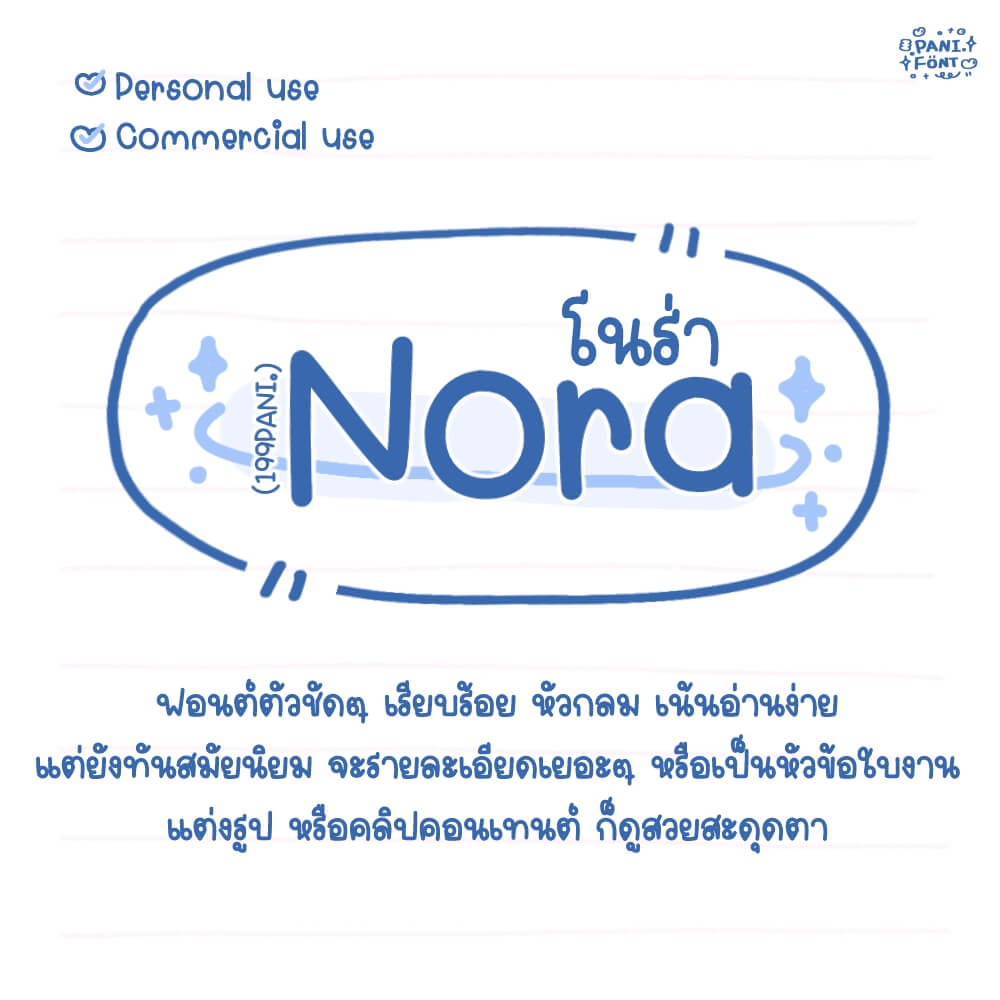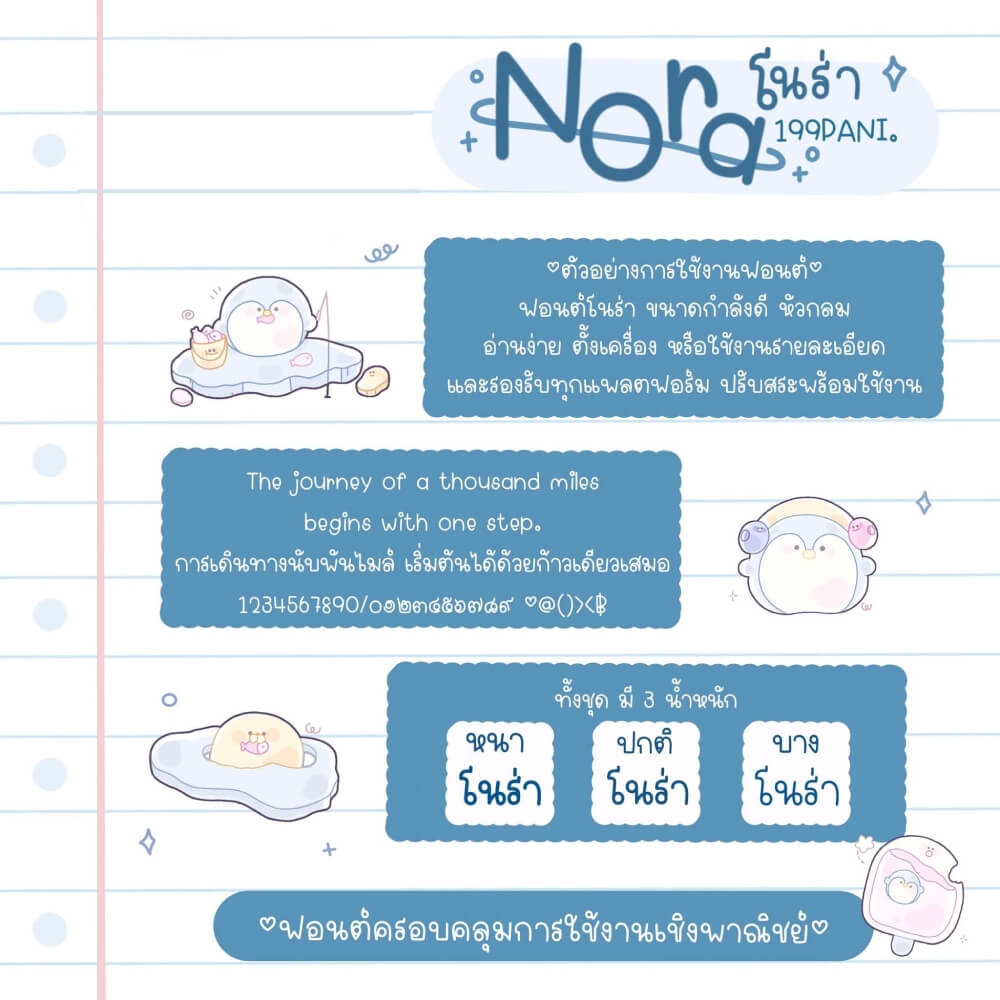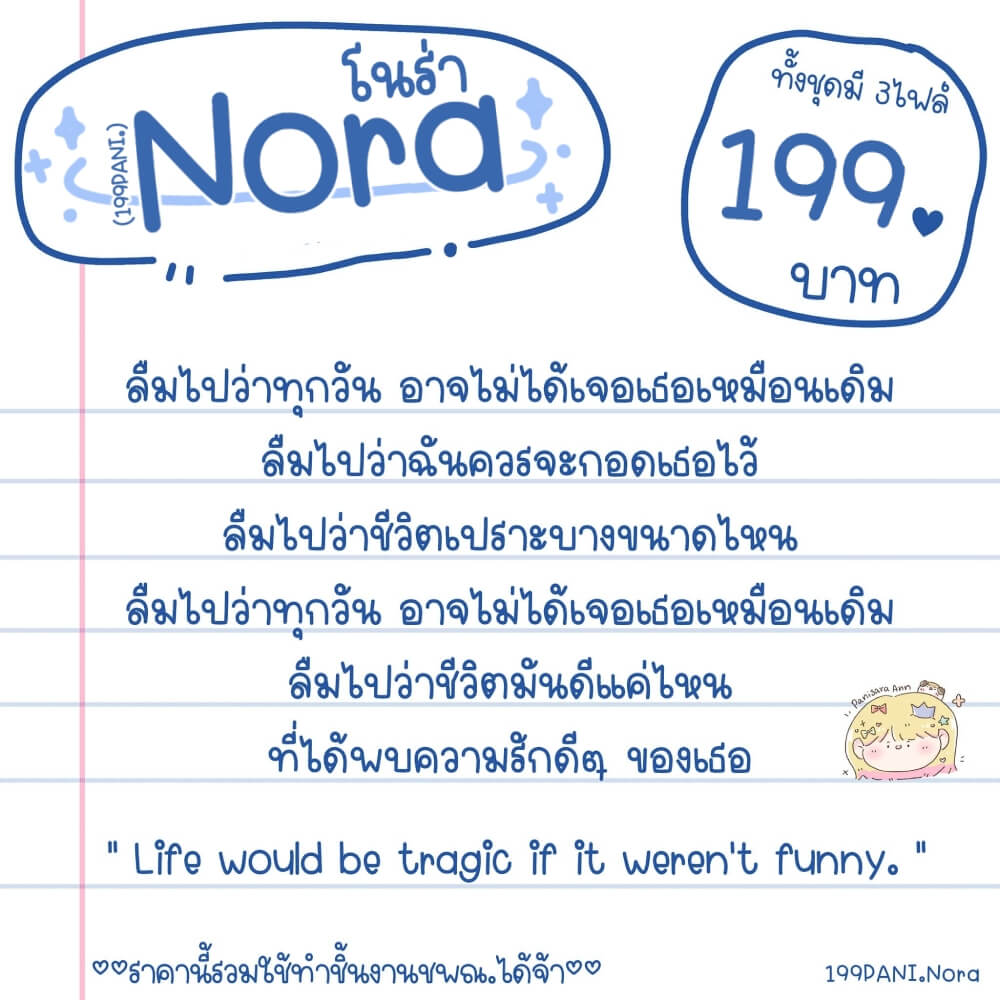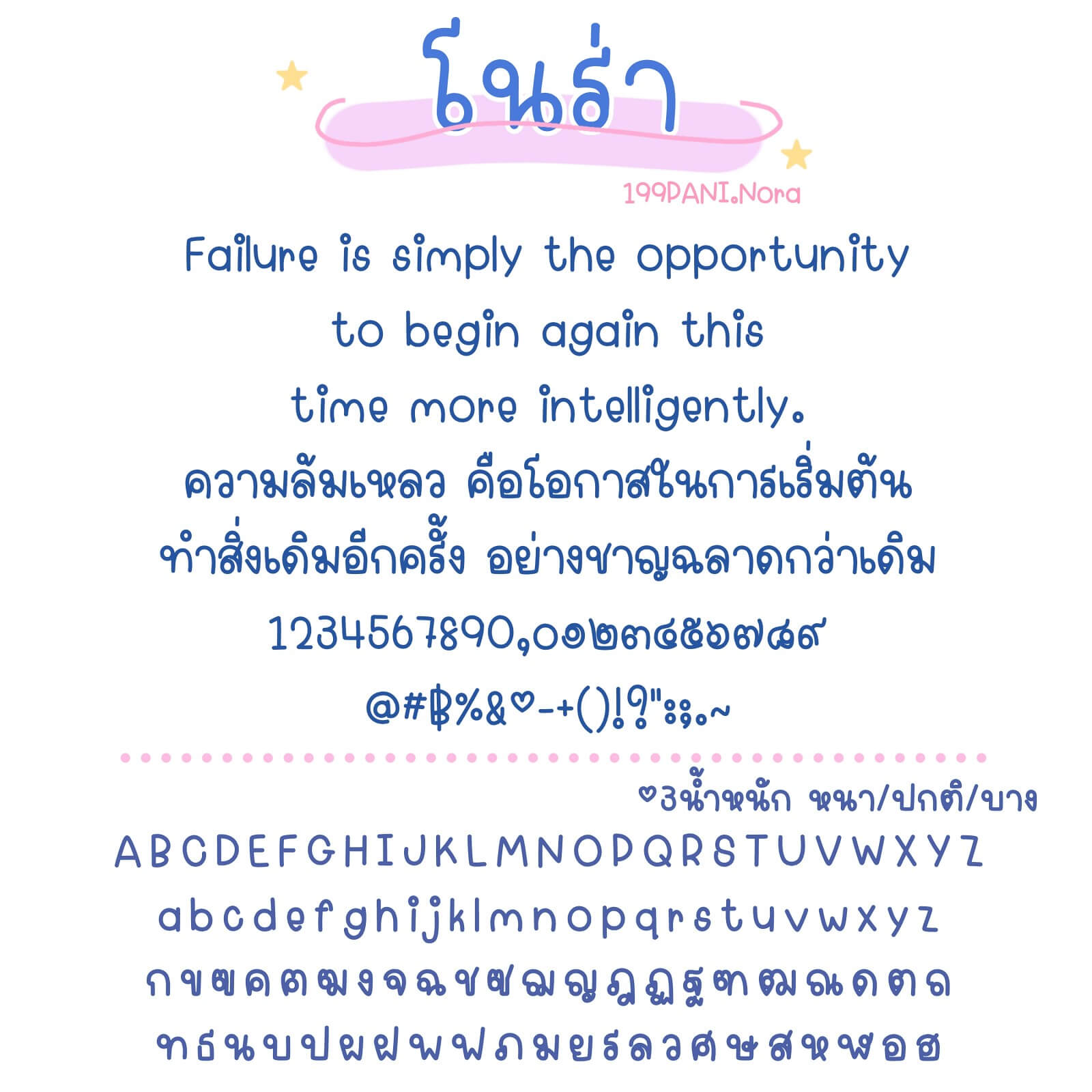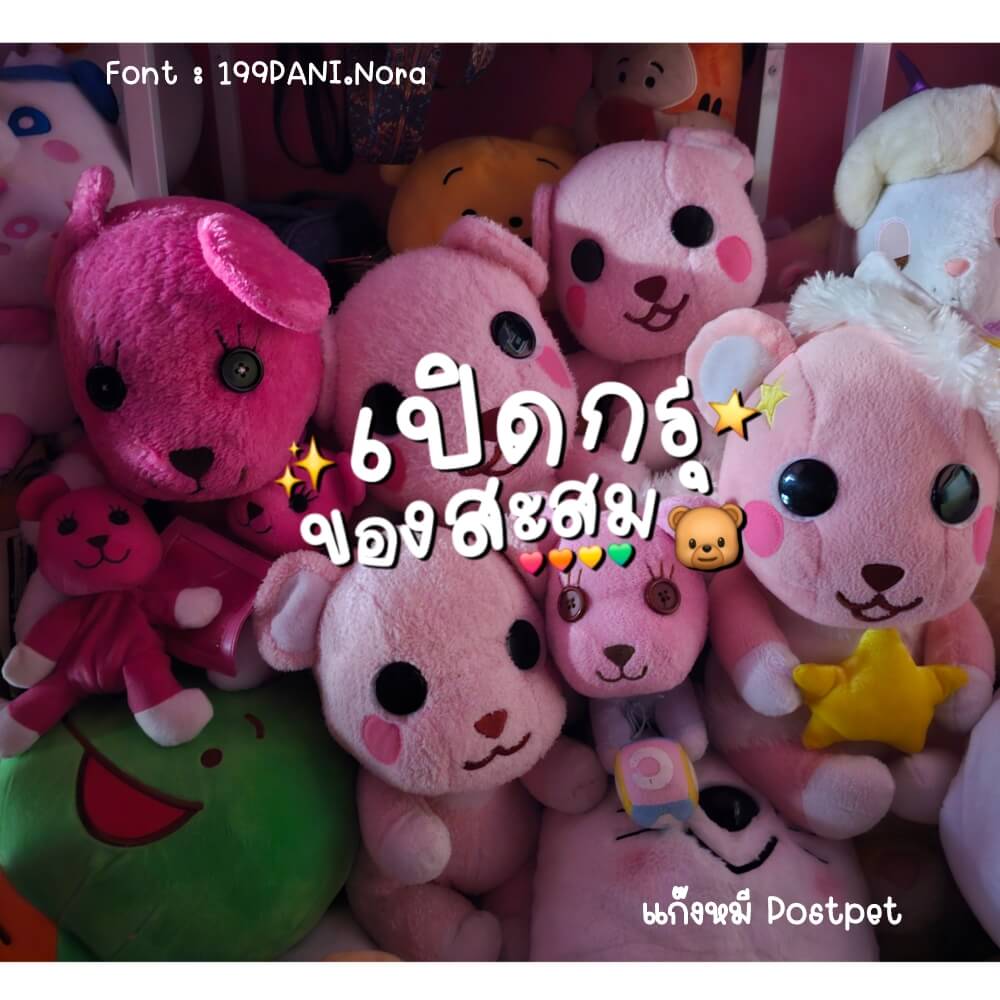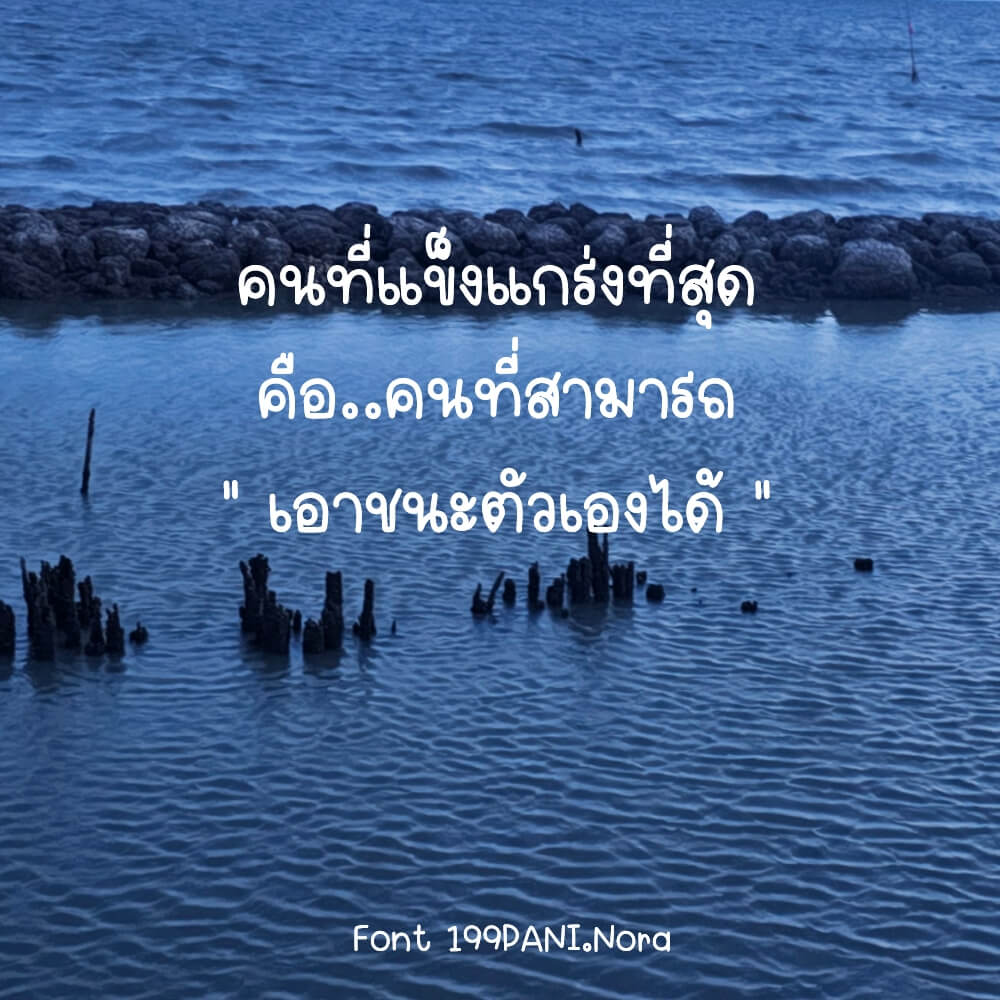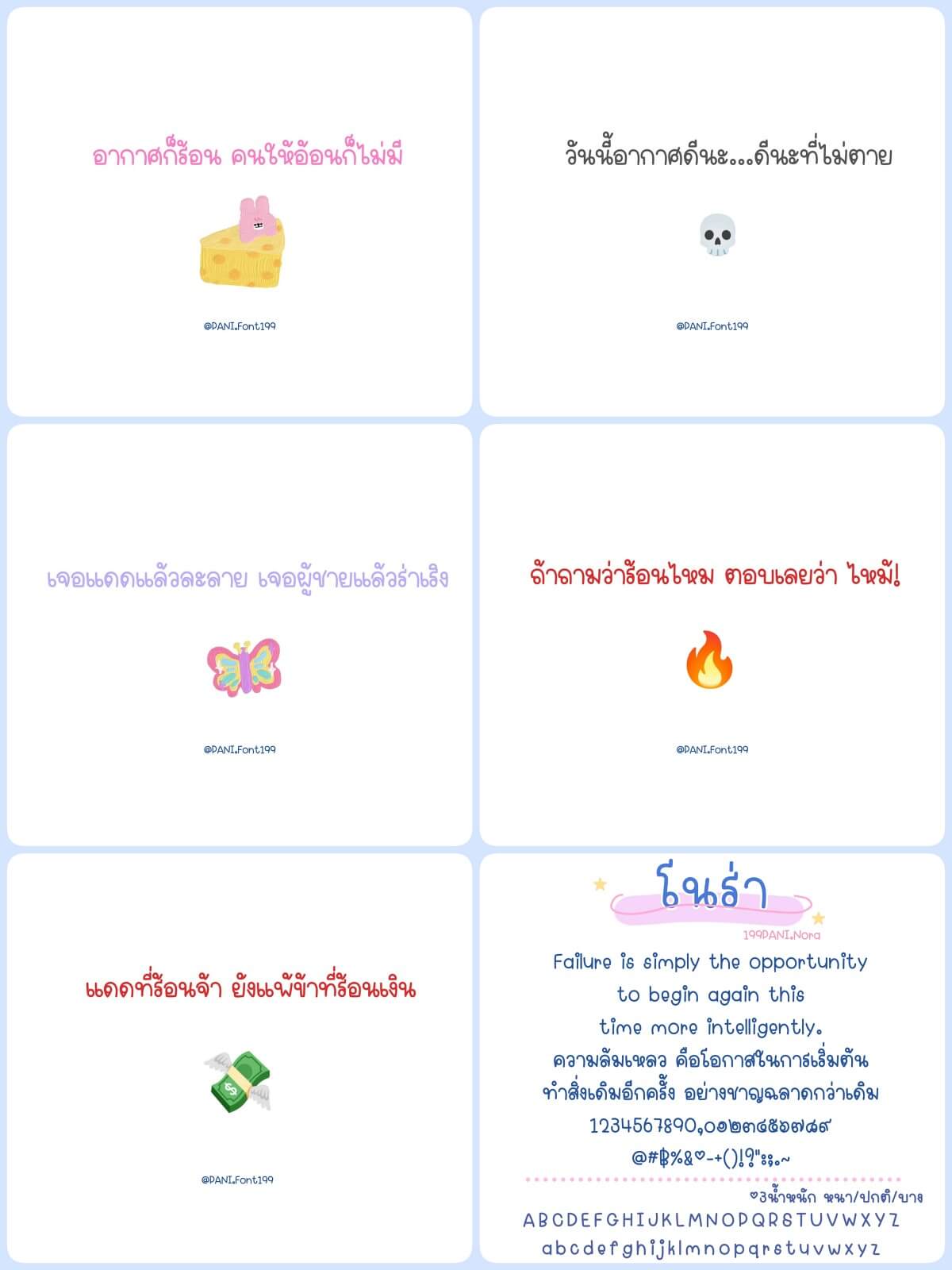
ฟอนต์ 199PANI.Nora – โหลดทดลองใช้ฟรีตัว Demo ฟอนต์ตัวชัดๆ เรียบร้อย หัวกลม เน้นอ่านง่าย แต่ยังทันสมัยนิยม จะรายละเอียดเยอะๆ หรือเป็นหัวข้อใบงาน แต่งรูป หรือคลิปคอนเทนต์ ก็ดูสวยสะดุดตา
199PANI.Nora